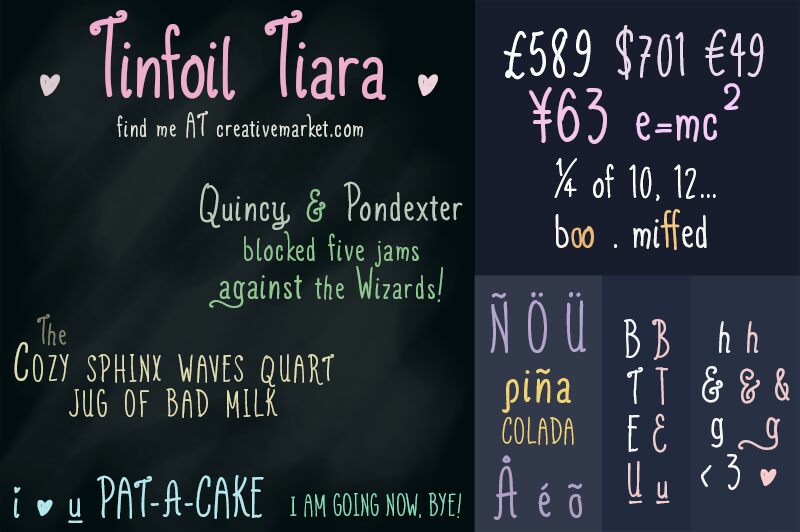
Inspiriert von hohen, schlanken Handschriften kommt mit Tinfoil Tiara eine Display-Schrift, die hübsch ist, aber ihre Ecken und Kanten hat.
Die Vollversion bietet kontextbedingte Alternativen für y, n, g & h (ein-/ausschaltbar über das Zeichen-Bedienfeld in Photoshop), besondere Einzelzeichen (ein i mit Herzpunkt etc.) sowie stilistische Alternativen für B, E, T & &. Zudem ist Unterstützung für internationale Zeichen enthalten.
Tinfoil Tiara DEMO